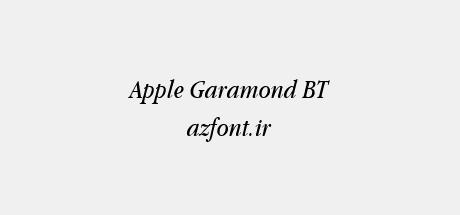
Apple Garamond BT
فونت زیبای رایگان Apple Garamond BT
قلم زیبای Apple Garamond BT Book Italic از سری قلم های بسیار زیبا برای تایپوگرافی و لوگو تایپ می باشد.این قلم در وزن Book Italic و توسط Boutros International 2015 طراحی و منتشر شده است.